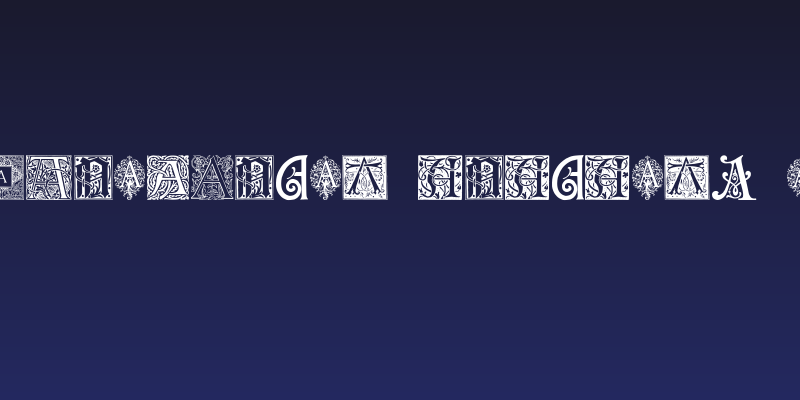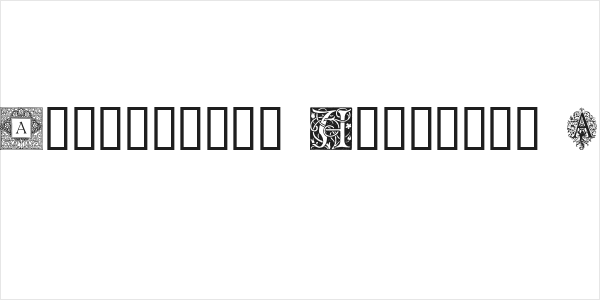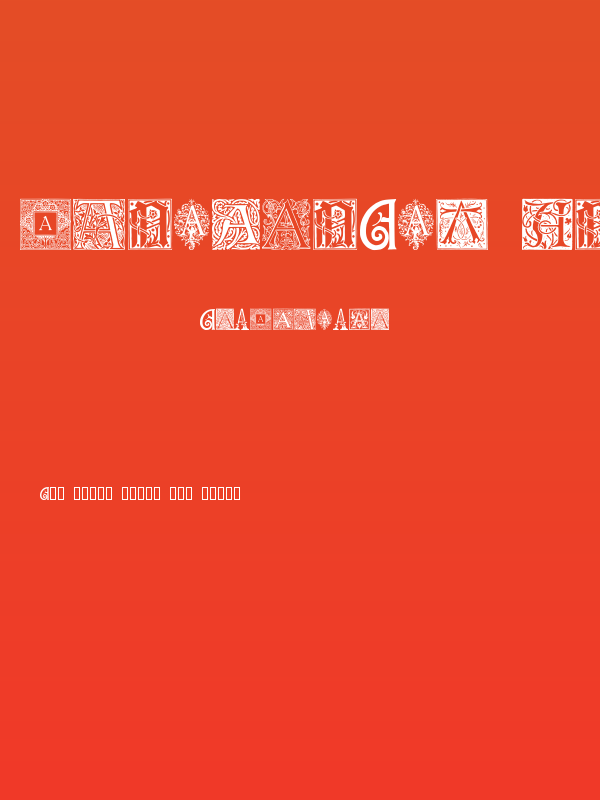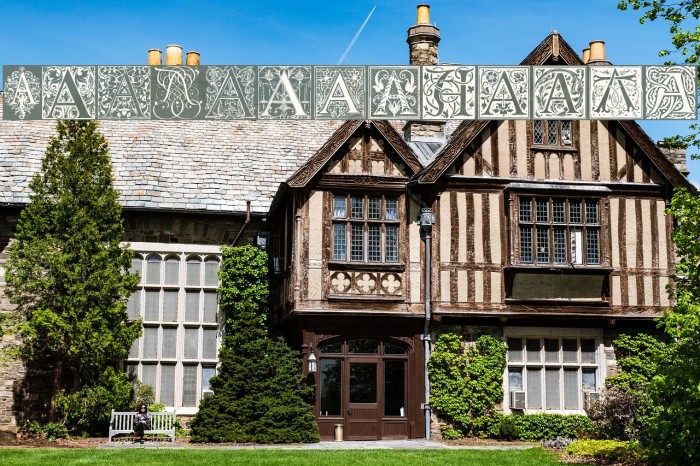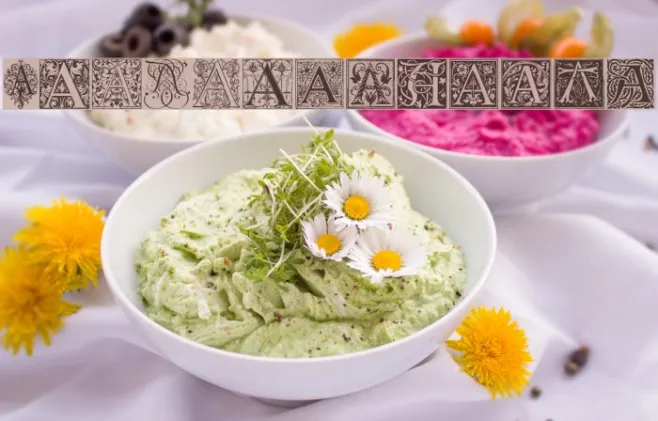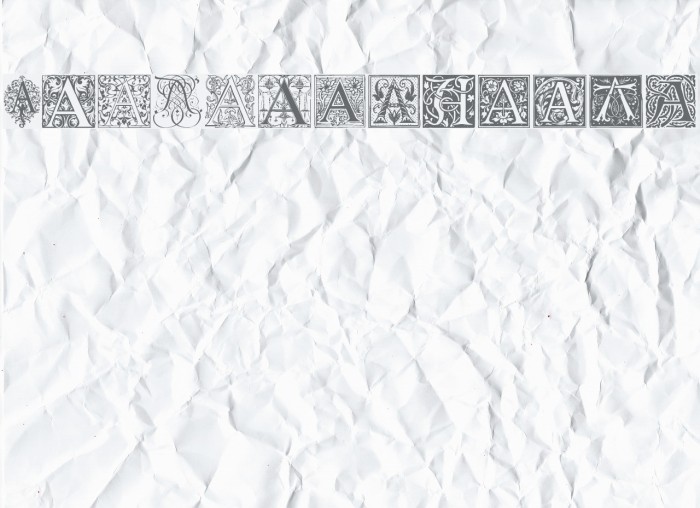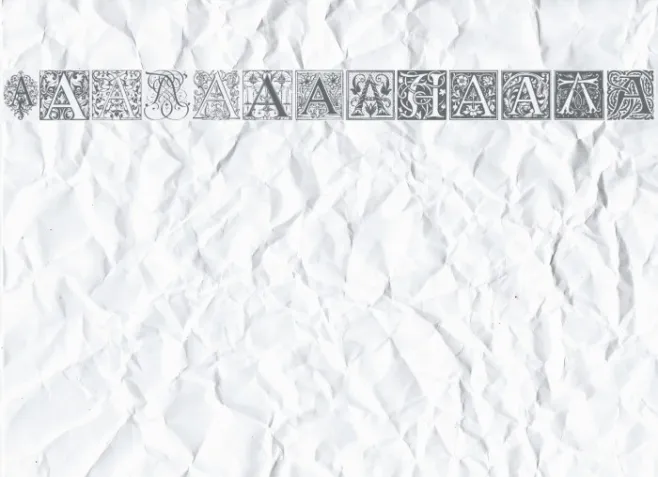
Ornamental Initials A Font
| Progetti proposti | Ideal for use in wedding invitations, book covers, greeting cards, and any project requiring a touch of elegance and historical charm. |